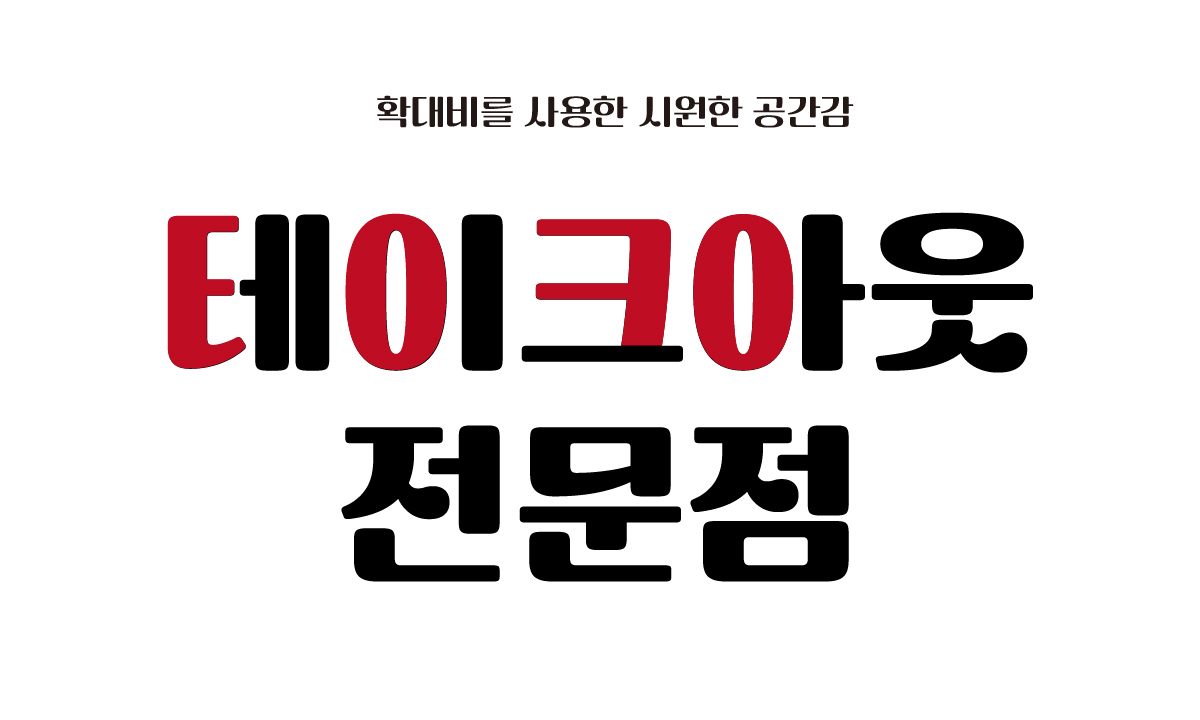
부대찌개 테이크아웃 전문점으로서 편리하고 친근한 이미지를 서체에 담아 전달하고자 첫 브랜드 폰트인 '땅스부대찌개체'를 만들었습니다. 땅스부대찌개체는 가족과 함께하는 따뜻한 식사처럼 편안하고, 안정적인 느낌을주는 실용성있는 폰트입니다. 땅스부대찌개체와 함께 당신의 이야기를 써내려가보세요!